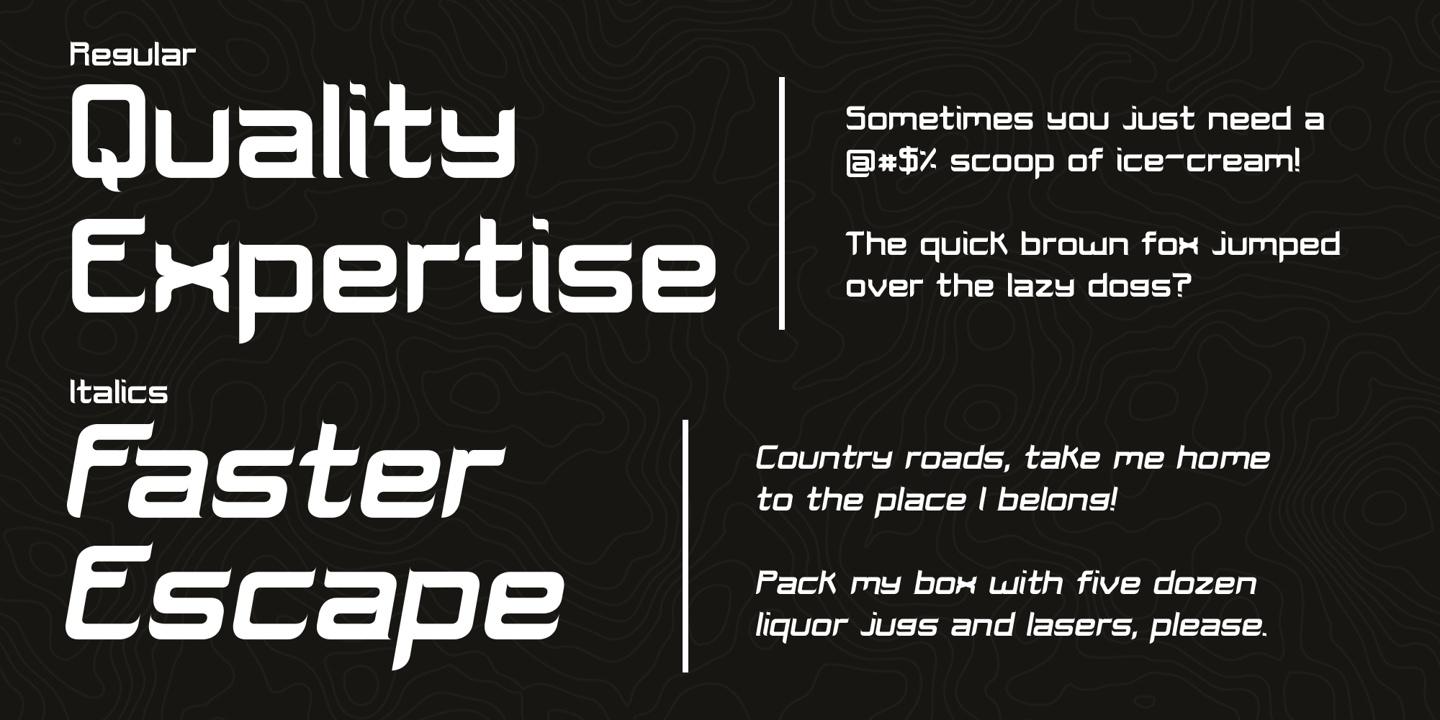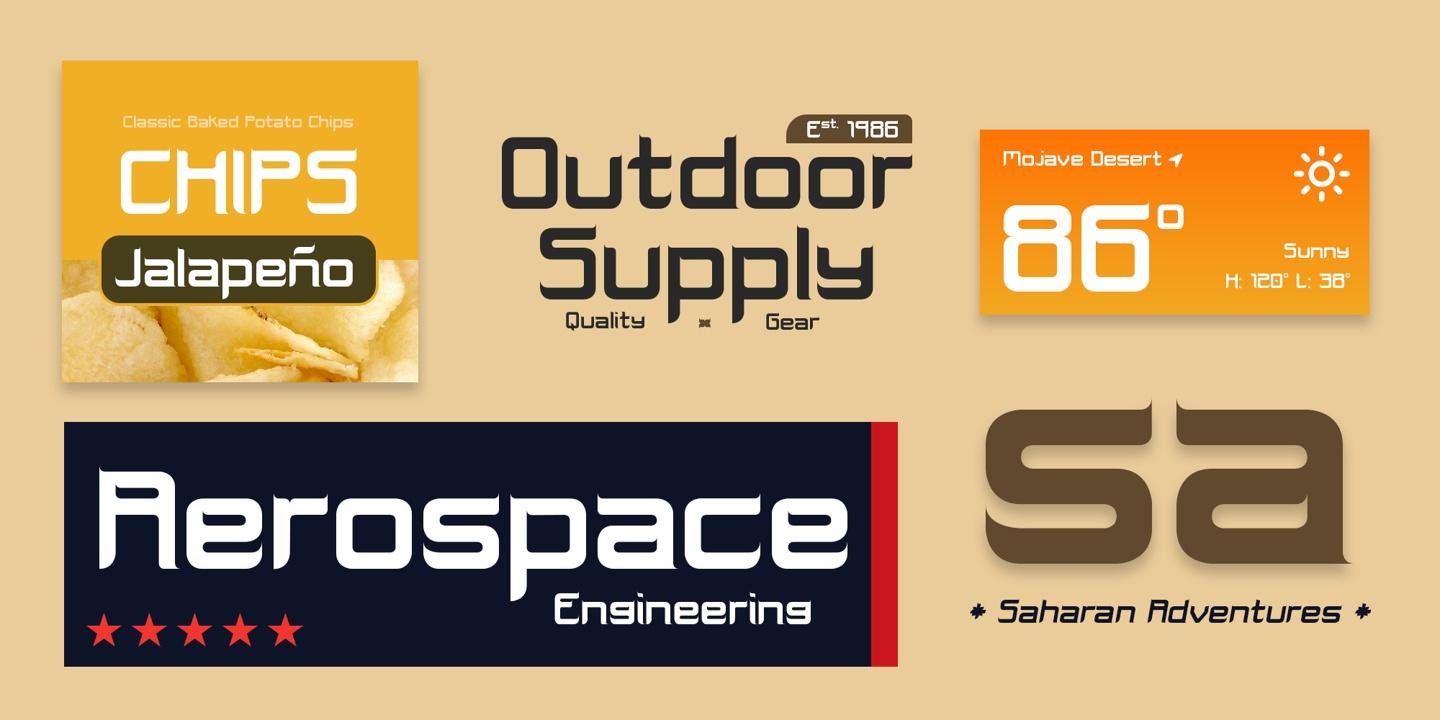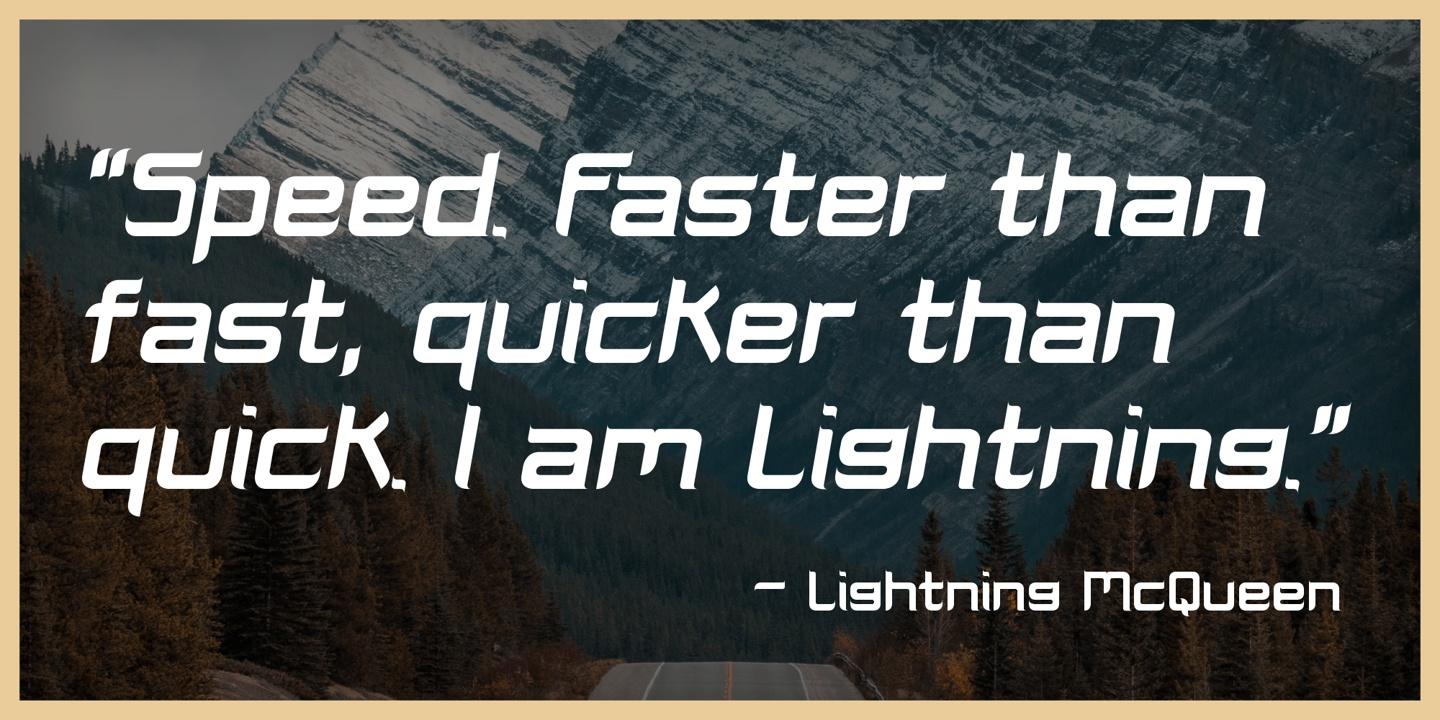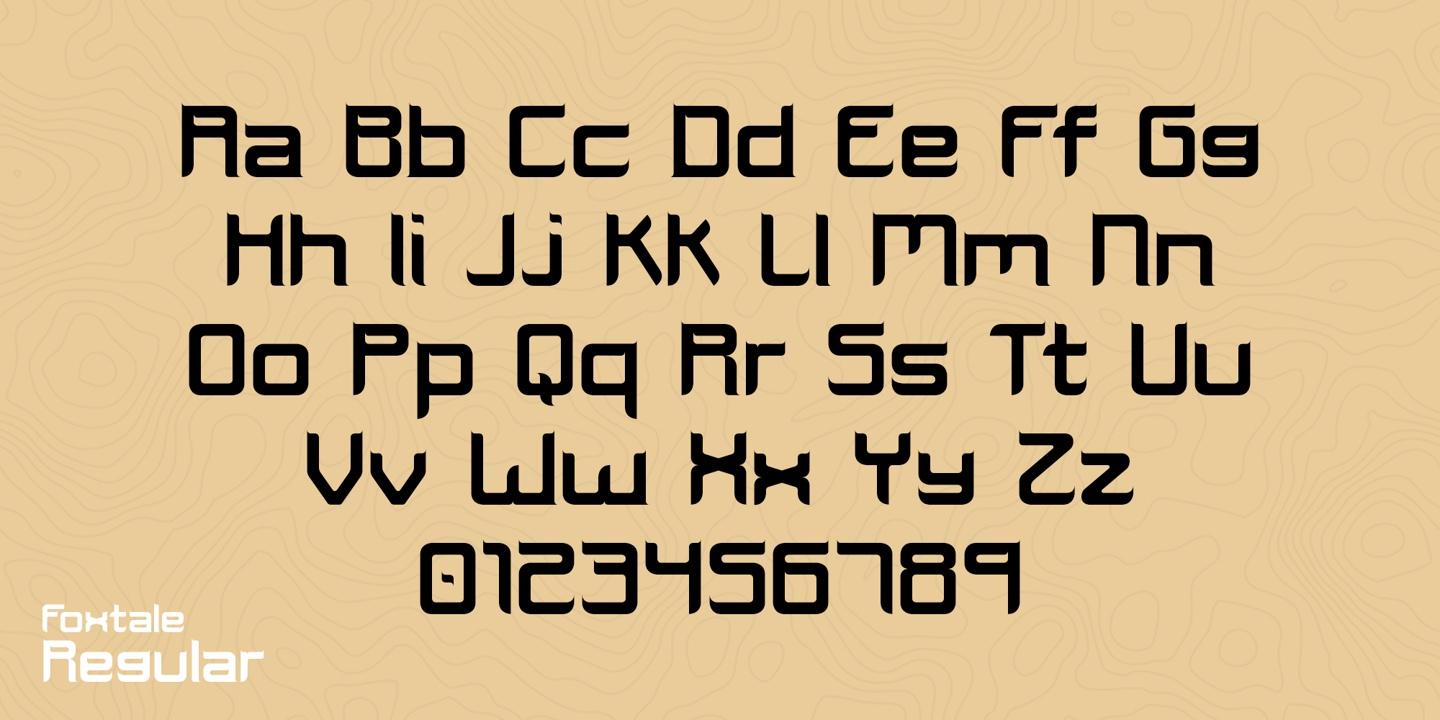
Foxtale Font Family
Foxtale s’inspire d’un ancien style scriptural hébraïque, avec des séraphins évasés, des structures classiques et des formes dramatiques. Foxtale est parfaitement adapté aux marques verbales ou aux sous-textes percutants. Une police de caractères complète avec des majuscules et des minuscules, des caractères latins, des chiffres, des symboles, des devises et des alternatives – Foxtale excitera sûrement votre prochaine aventure de design !